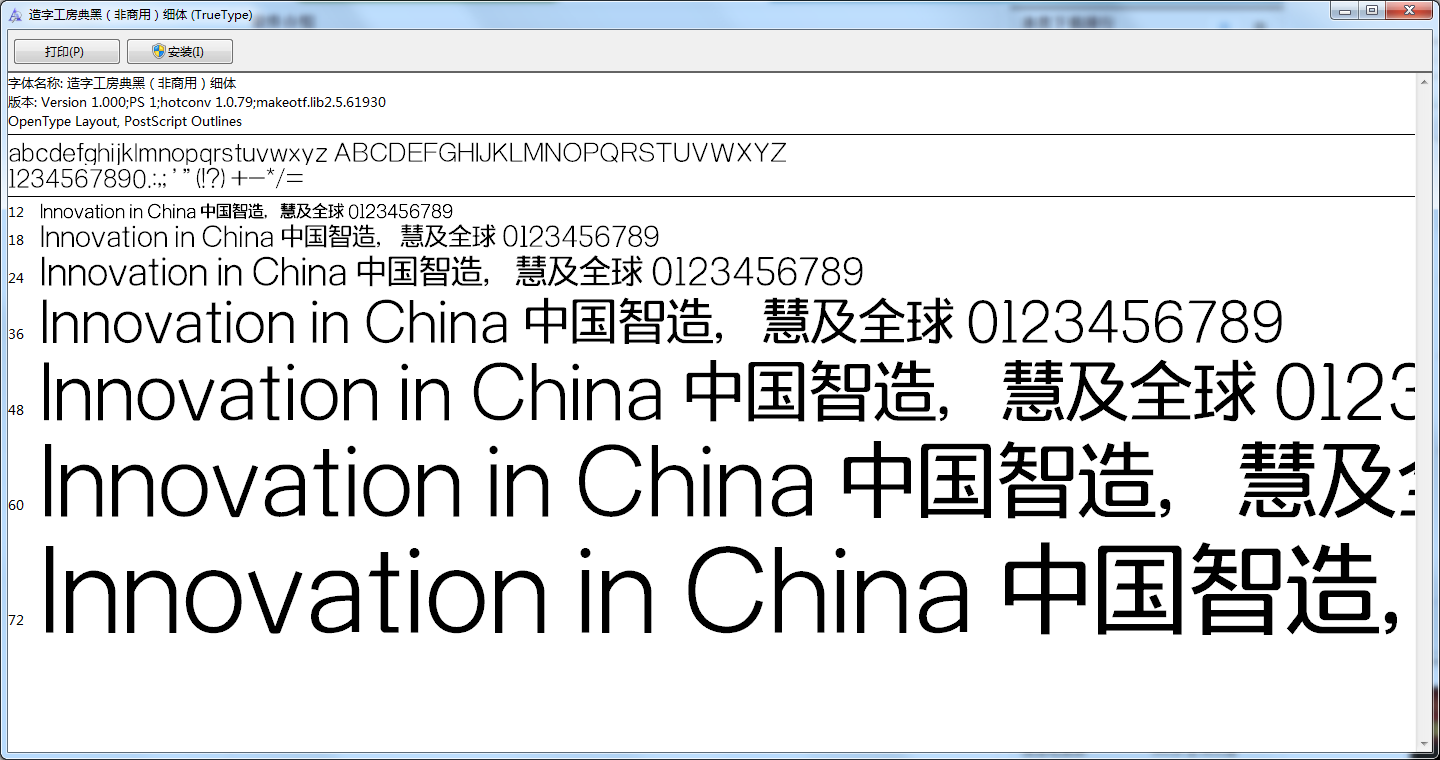
造字工房典黑字體是一款字體應用,包含造字工房典黑常規(guī)體、粗體、超粗體以及造字工房典黑細體、纖細體、特細體、超細體共7款字體。造字工房典黑體,字形方正嚴謹、筆畫簡潔有力、中宮清晰,在黑體字形基礎之上巧妙創(chuàng)新,使其字形筆畫柔和而不失剛毅,風格鮮明且極具易讀性。適用于文字標題、廣告設計乃至正文等視覺環(huán)境,有著極強的應用空間。
1.造字工房典黑體,字形方正嚴謹、筆畫簡潔有力、中宮清晰,在黑體字形基礎之上巧妙創(chuàng)新。
2.字形筆畫柔和而不失剛毅,風格鮮明且極具易讀性。
3.包含造字工房典黑常規(guī)體、粗體、超粗體以及造字工房典黑細體、纖細體、特細體、超細體共7款字體。
4.主要適用于文字標題、廣告設計乃至正文等視覺環(huán)境。